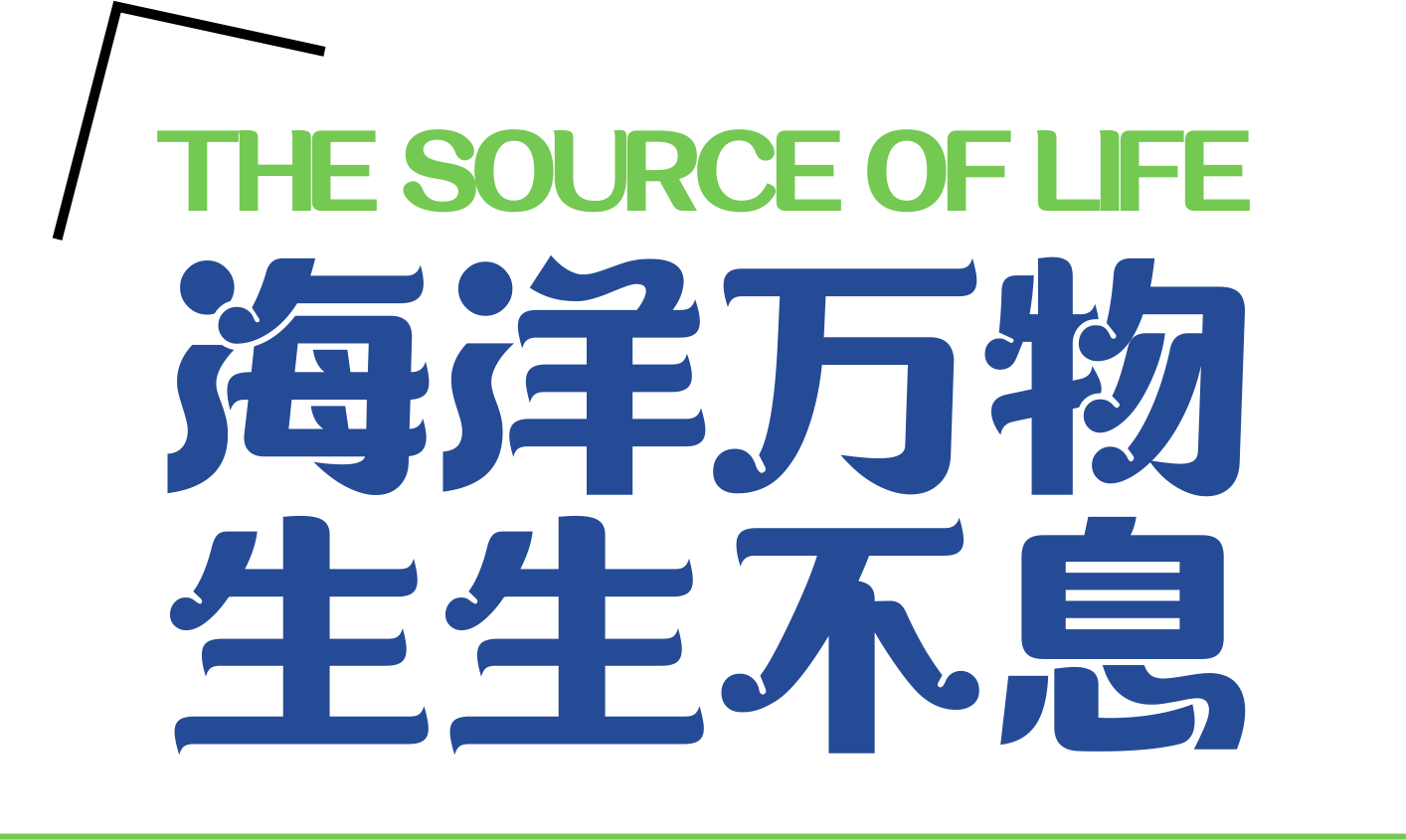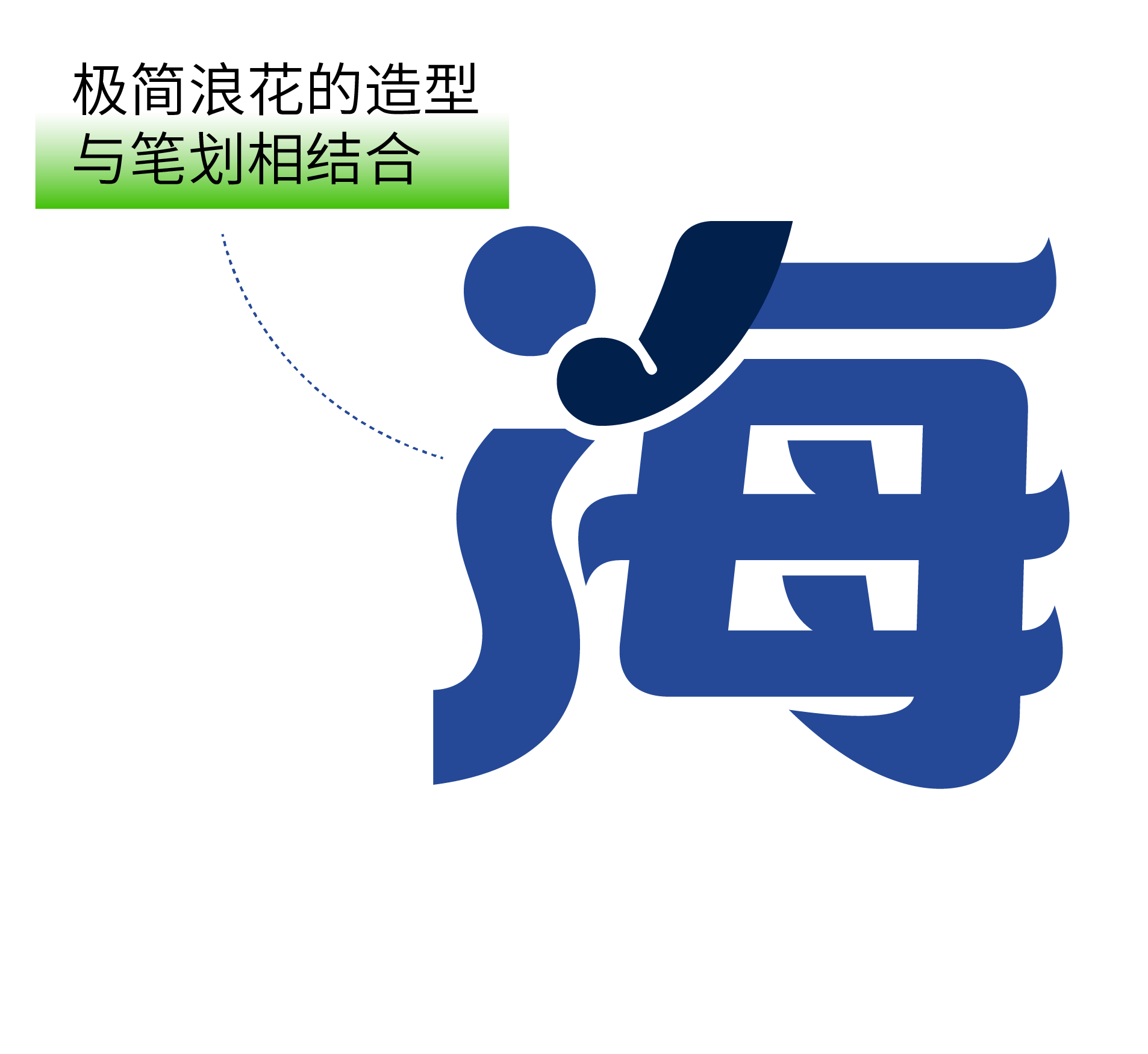
向下游动
深入神秘的蓝色国度
海洋,常常给人孤独的印象
因为它的面积覆盖了地球70%以上
而人类对它的探索仅有5%
但它其实从来不寂寞
因为有无数的生灵
世世代代在那里繁衍生息
海洋里伟岸的歌唱家
拥有极高的智商与丰富的情感
它们的每一次游动
都在促进营养物质的运输与循环
当在最后的时刻沉入深海
鲸落的抵达托举起了生命绿洲
这些顶级掠食者常给人残酷的印象
但淘汰病弱个体
和压制单一物种数量激增
正是它们守护海洋的方式
看似无情的背后
是鲨鱼不为人知的温柔
海洋里古老的建筑师
其构筑的彩虹城堡
不仅是海洋里一道绚烂的风景
更为无数鱼群提供了庇护地
在约0.1%的海底面积上,养育了至少1/4的海洋生命
你知道吗?大海拥有神奇的自愈力。
它在提供丰富资源的同时,也让海洋种群稳定地存续。
然而,人类过度的索取,已让这片蔚蓝日渐疲惫,难以快速恢复往日的生机。
作为海洋科普与生态保护的倡导者,海昌海洋公园长期致力于极地海洋生物保育、濒危救助和繁育。其参与救助并放生的搁浅短肢领航鲸“海棠”,是中国首例成功救助的短肢领航鲸案例。
截至目前,海昌海洋公园已累计协助救助水生生物100余只,其他小型珍稀生物1800余只。
借由与海昌海洋公园的跨界合作,我们期望能够唤起人们对海洋更多的关注与保护。
我们提取了人们心中描绘海洋的关键词,并将其融入独特的字体设计之中,期望在一笔一画间,重新搭建人与自然的共鸣。
“我们如此热爱这片奇迹之地,
每一个来自深海的灵感
都成为这款字体诞生的契机”
字体特征
在字体形态的构建中,我们深度解构了海洋生态的有机美学。设计团队采撷以海浪造型与海洋生物的优雅线条,用设计语言将其进行转化、再创造,使字里行间涌动着潮汐般的节律。我们希望将蔚蓝领域的天然之美与生命力量,通过笔触抵达人们的心中。
每个笔画都延续了疗愈海洋的叙事线索,横竖撇捺如同海平面上的温柔起伏,细节处甚至能看到”水花溅起“,蕴含着抚平海洋之伤的美好心愿。
海洋制造了大量的氧气,我们的每一次呼吸,都呼应着海洋的心跳。
仿若海浪褪去后岸边的简洁留白,我们特意在笔画重叠处做了剪切处理,赋予字体来自空间律动的生命力与治愈感。
人与自然本来就共生共融
将来自海洋的设计应用于日常
使得文字在传递信息的同时
也能成为可持续理念的载体
宣传海报
字体应用